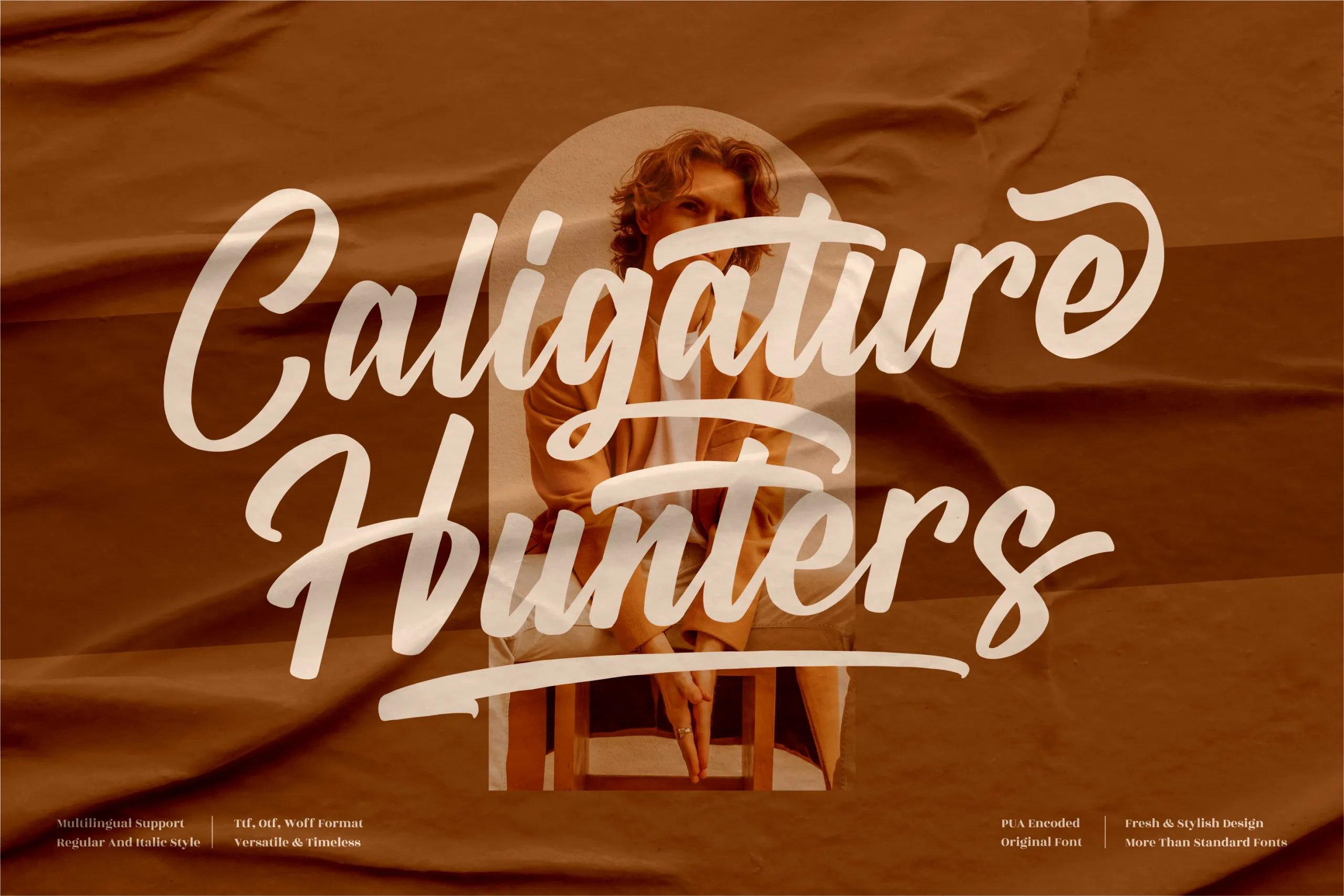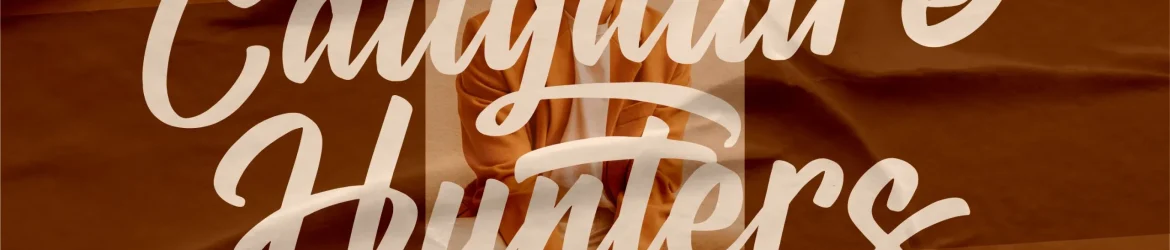
Caligature Hunters Font – Download Grátis
A Caligature Hunters é uma fonte de签字,desenvolvida especialmente para os projetos mais luxuosos e sofisticados que exigem a perfeição de uma assinatura premium. Esta fonte especializada não apenas trará um toque único aos seus trabalhos, mas também permitirá que você personalize suas criações com o sabor autêntico da签字,uma arte rica que remete às habilidades artísticas do passado. Ideal para qualquer projeto onde deseja adicionar um toque de elegância e sofisticação, desde a desenvolvida identidade de marca até as embalagens dos produtos. Eles são perfeitos para criações como logotipos, design de móveis de casa, embalagens de produto, tigelas personalizadas, citações em cartazes ou posters, sacolas e camisetas promocionais, capas de livros, cartões de nome, cartões de convite, cartões de agradecimento, etiquetas, fotografia, marca d’água para eventos especiais. Eles são perfeitos para todos os seus projetos de luxo que exigem um sabor premium da签字,uma arte e habilidade artística do passado.